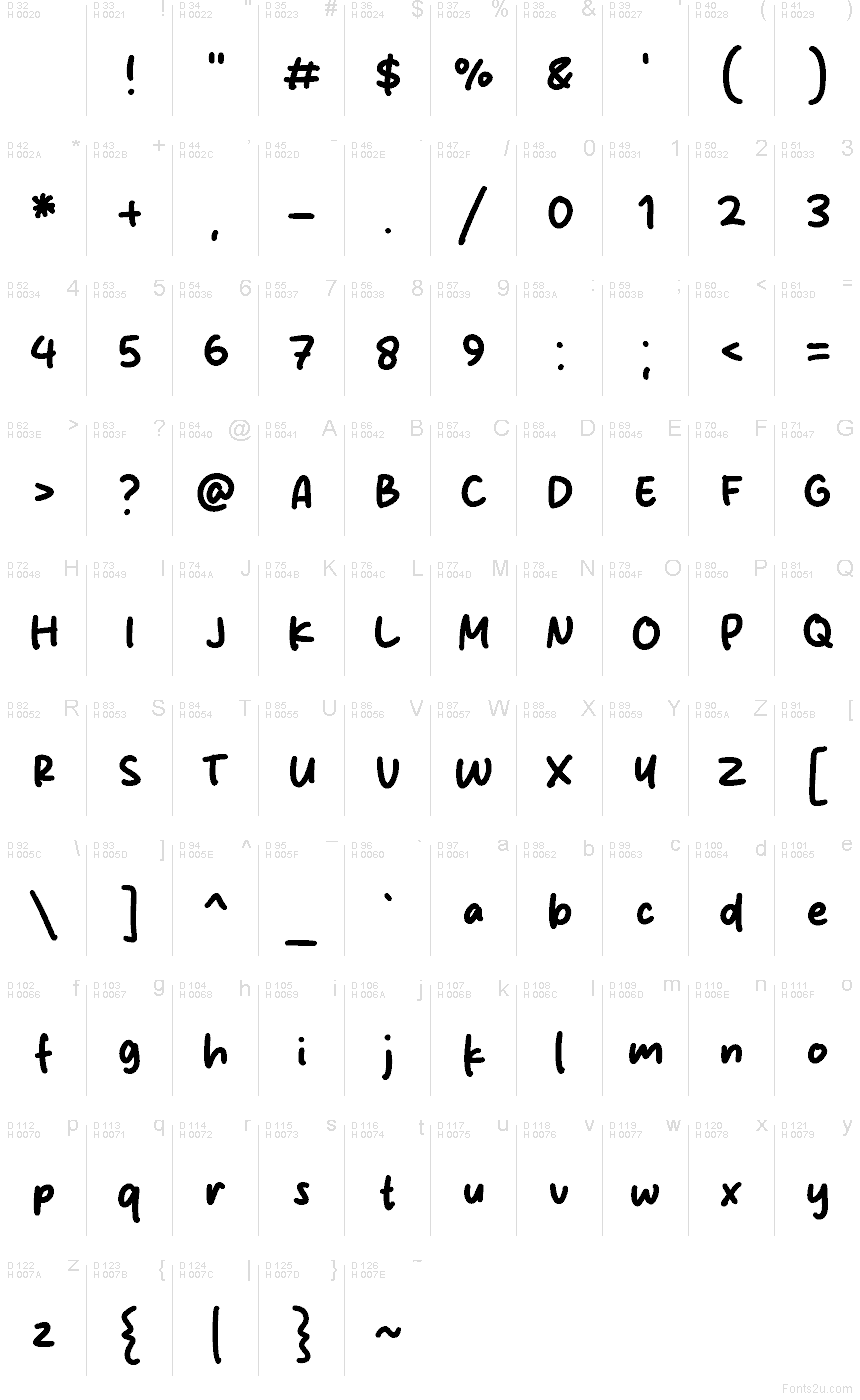
Delecius Chilli von MJType ist eine kostenlose, handgeschriebene Pinselschrift mit einem lässigen Rhythmus, kräftigen Strichen und sanft abgerundeten Kurven. Die Buchstaben wirken lebendig und freundlich, nicht poliert, und verleihen kurzen Wörtern durch ihren leichten Schwung und die kompakten Kurven eine persönliche Note.
Diese Schrift eignet sich hervorragend für das Branding von Cafés und Lebensmitteln, Social-Media-Zitate, Verpackungen, Plakatüberschriften und Cover-Texte im Scrapbook-Stil, bei denen eine entspannte, handschriftliche Anmutung die Botschaft unterstreicht. Als kostenlose Schriftart passt sie zudem perfekt für Titelkarten, kurze Kampagnenmotive sowie Namen oder Initialen, da die ausgeprägte Pinseltextur selbst kurzen Texten eine warme und präsente Wirkung verleiht.